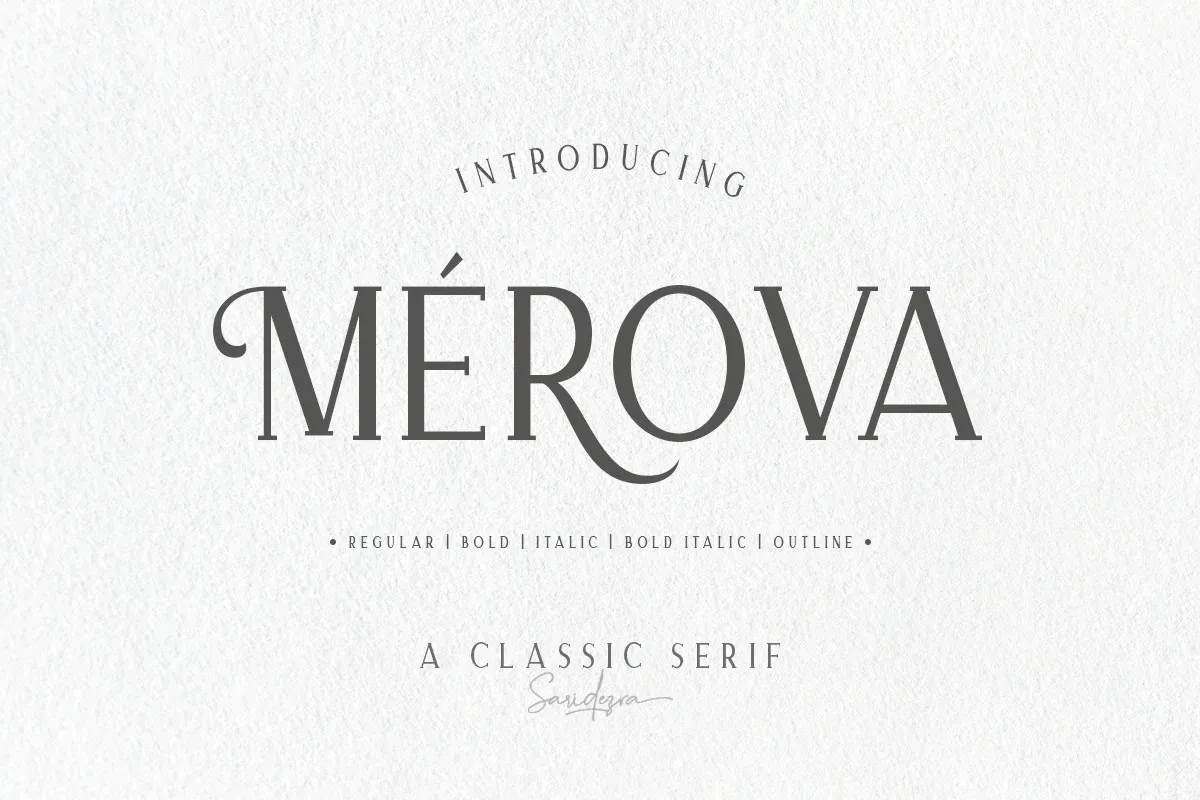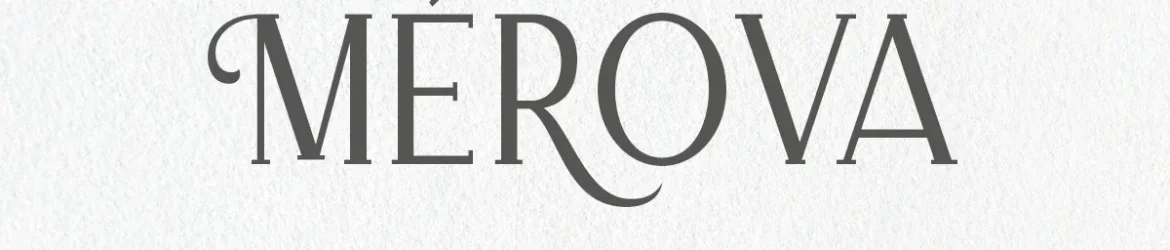
Merova Font é uma elegante fonte serif que traz um toque moderno e sofisticado à sua apresentação ou logomarca. Suas letras em minúsculo com alternativas para cada caractere, incluindo opções alternativas em forma vintage, tornam seu design ainda mais atraente e único. Esta fonte é especialmente adequada para quem busca uma solução de tipo que se destacará em qualquer contexto. Além disso, Merova suporta múltiplas línguas, oferecendo flexibilidade e versatilidade ao longo do mundo. Com seu código PUA já pré-estabelecido, você pode garantir um download seguro da fonte. Inspirada na elegância de tempos passados mas atualizada com uma nova era de design, Merova é a escolha perfeita para quem valoriza tanto a classe quanto o frescor moderno em seu trabalho gráfico.